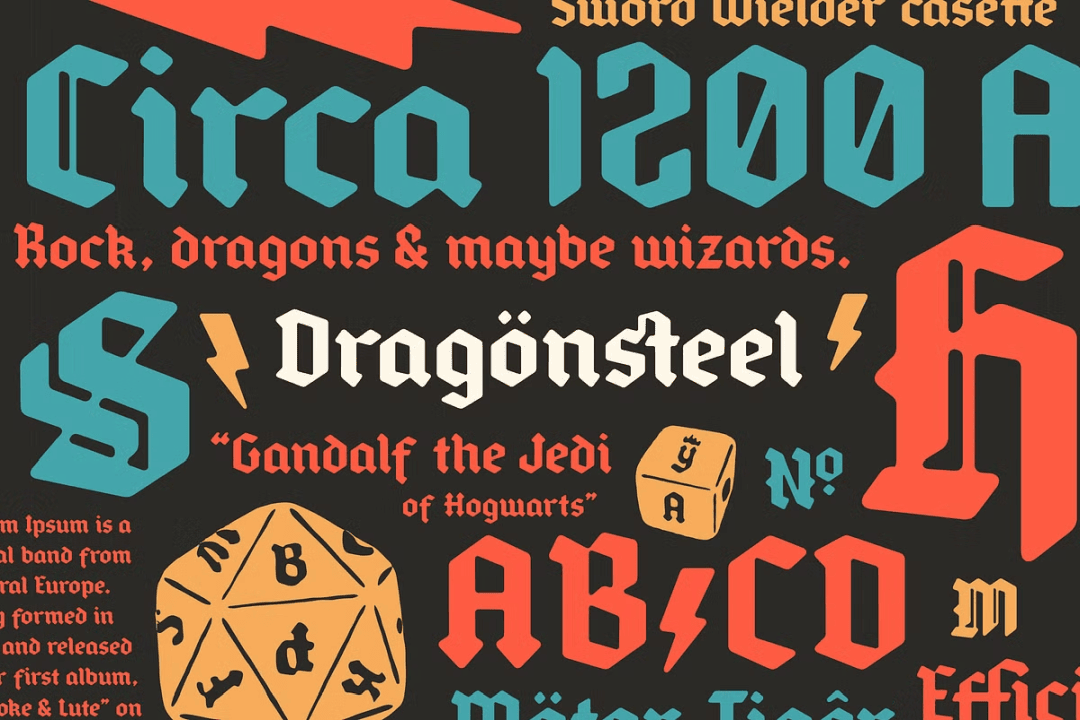
Dragönsteel
現代風にアレンジされたブラックレターディスプレイ。カリグラフィー書体のブラックレター(ゴシック)の装飾を軽めにシンプルにし、現代にマッチするようアレンジされた書体。ちゃんとブラックレターの雰囲気は残しつつ、可読性が多少向上しているのが見て取れるだろう。’80年代の RPG にインスパイアされたものとのこと。ややアウトラインが丸くなっているが、さらに丸くなった Rough、角をきっちり出した Sharp の3種類がある。クリスマスよりはハロウィーンに似合ったかな…?